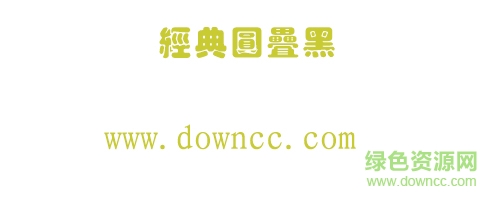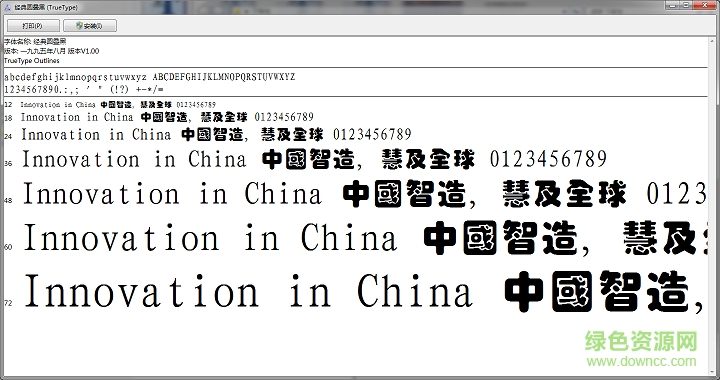
經(jīng)典圓疊黑是一款繁體字體。該字體最大的特點(diǎn)就是方正,并且筆畫比較粗,給人非常正直的感覺。下載字體后能讓自己的寫字手法變得更加新穎。喜歡就來綠色資源網(wǎng)下載吧!
最常用的簡(jiǎn)體中文字體,該字體粗壯有力,字形端正大方,字庫完整,并且整體效果非常出眾,可應(yīng)用于雜志報(bào)刊、文學(xué)創(chuàng)作、平面廣告、印刷包裝等領(lǐng)域